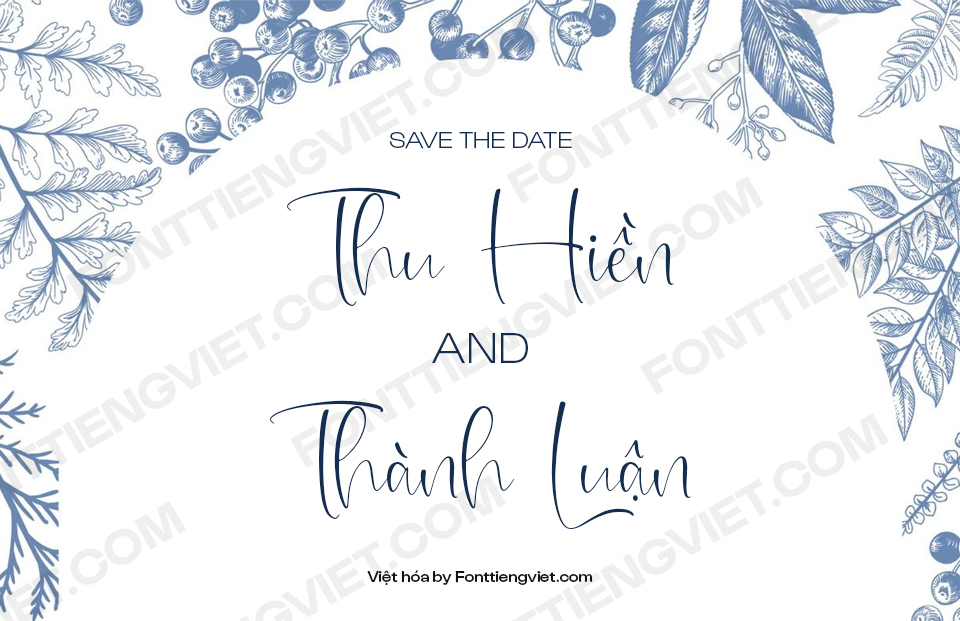
Font Việt hóa 1FTV VIP Sparkle Perfection – Font thiệp cưới
Font Việt hóa 1FTV VIP Sparkle Perfection – Font thiệp cưới sang trọng và tinh tế
Trong lĩnh vực thiết kế đồ họa sự kiện, việc lựa chọn Font Miễn Phí phù hợp đóng vai trò then chốt để tạo nên linh hồn cho tác phẩm. Một trong những lựa chọn hàng đầu hiện nay chính là Font Việt hóa 1FTV VIP Sparkle Perfection – Font thiệp cưới. Đây là bộ font chữ được thiết kế riêng biệt nhằm tôn vinh vẻ đẹp lãng mạn, thanh lịch và không kém phần hiện đại cho các mẫu thiệp mời cao cấp. Với các đường nét uyển chuyển và bộ ký tự đa dạng, font chữ này không chỉ giúp nội dung trở nên dễ đọc mà còn tạo ấn tượng thị giác mạnh mẽ ngay từ cái nhìn đầu tiên đối với người nhận thiệp.
Đặc điểm nổi bật của Font Việt hóa 1FTV VIP Sparkle Perfection – Font thiệp cưới
Đường nét thanh mảnh và nghệ thuật
Bộ Font Việt hóa 1FTV VIP Sparkle Perfection – Font thiệp cưới sở hữu cấu trúc các nét thanh và nét đậm được kết hợp một cách hài hòa. Những đường cong uốn lượn mang đậm chất nghệ thuật thư pháp hiện đại, giúp thông điệp tình yêu trong ngày trọng đại trở nên ngọt ngào hơn. Các nhà thiết kế thường ưu tiên sử dụng bộ font này cho phần tên cô dâu chú rể hoặc các tiêu đề quan trọng nhờ khả năng hiển thị mượt mà trên nhiều chất liệu in ấn khác nhau.
Khả năng tương thích và tối ưu hóa tiếng Việt
Điểm cộng lớn nhất của phiên bản này chính là việc đã được việt hóa hoàn chỉnh. Người dùng sẽ không gặp phải các lỗi hiển thị dấu câu khó chịu thường thấy ở các bộ font ngoại nhập. Mọi ký tự đặc trưng của tiếng Việt như “đ”, “ơ”, “ư” hay các dấu thanh đều được tinh chỉnh tỉ mỉ để giữ đúng tinh thần nguyên bản của thiết kế Sparkle Perfection, đảm bảo tính thẩm mỹ đồng nhất cho toàn bộ văn bản thiết kế của bạn.
Ứng dụng thực tế của font chữ trong thiết kế hiện đại
Thiết kế thiệp cưới và thiệp mời sự kiện
Đúng như tên gọi, Font Việt hóa 1FTV VIP Sparkle Perfection – Font thiệp cưới là “ngôi sao” trong các bản thiết kế thiệp mời. Dù bạn theo đuổi phong cách cổ điển, hoàng gia hay tối giản, bộ font này đều có thể biến hóa linh hoạt. Khi kết hợp với các hiệu ứng ép kim hoặc dập nổi trên giấy mỹ thuật, các nét chữ sẽ tạo nên hiệu ứng bắt sáng cực kỳ sang trọng, đúng với ý nghĩa “Sparkle” (lấp lánh) mà nhà sáng tạo mong muốn truyền tải.
Sử dụng trong branding và truyền thông xã hội
Ngoài thiệp cưới, bạn cũng có thể ứng dụng font chữ này vào việc thiết kế logo cho các tiệm áo cưới, studio chụp ảnh hoặc làm quote trên hình ảnh Facebook, Instagram. Sự tinh tế của bộ chữ giúp nâng tầm giá trị thương hiệu, tạo cảm giác chuyên nghiệp và tận tâm. Đối với các bạn học sinh, sinh viên yêu thích thiết kế, đây cũng là công cụ tuyệt vời để thực hiện các bài tập liên quan đến trình bày văn bản nghệ thuật hoặc làm thiệp chúc mừng thầy cô, bạn bè.
Kết luận về bộ font chữ Sparkle Perfection
Với sự kết hợp hoàn hảo giữa thẩm mỹ và tính ứng dụng, Font Việt hóa 1FTV VIP Sparkle Perfection – Font thiệp cưới xứng đáng có mặt trong bộ sưu tập của mọi designer. Nó không chỉ đơn thuần là những ký tự vô hồn mà còn là phương tiện truyền tải cảm xúc trọn vẹn nhất. Hy vọng qua bài viết này, bạn đã tìm thấy cảm hứng để tạo nên những mẫu thiết kế tuyệt đẹp. Hãy truy cập ngay trang web Font Miễn Phí, Font Việt Hóa, Font Việt hóa 1FTV VIP Sparkle Perfection – Font thiệp cưới để khám phá thêm nhiều tài nguyên hữu ích khác cho công việc sáng tạo của mình mỗi ngày.